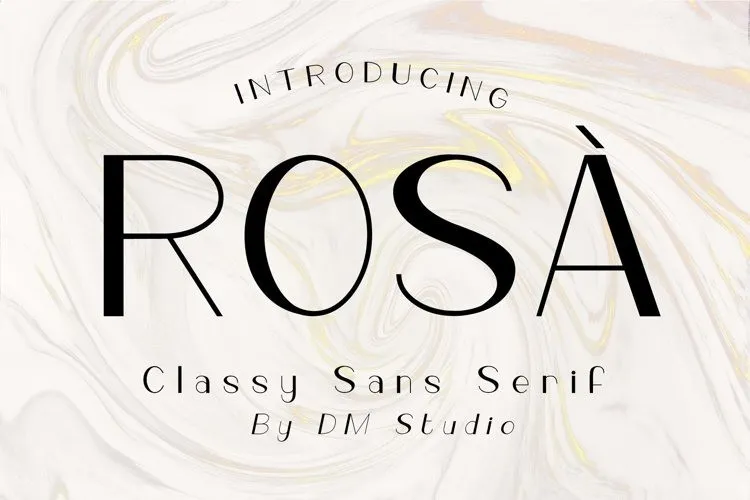
A Rosà Sans Serif Font é uma elegante seleção para designers atentos ao estilo moderno. Desenhada por dmletter31, esta fonte sans-serif traz cada letra cuidadosamente desenvolvida para manter seu texto único e chamativo. Com linhas limpas e desenhadas com cuidado, ela se destaca em diversos formatos de logotipos, marcas, headlines e templates, adaptando-se perfeitamente a qualquer tópico de marketing ou propaganda. Seja você um criador de logomarcas sofisticados ou simplesmente buscando adicionar um toque fresco à sua próxima peça editorial, Rosà Sans Serif Font oferece uma solução para todos os seus desafios de design. Além disso, a fonte tem duas versões disponíveis: regular e itálica, permitindo que você escolha a opção que melhor se adequa ao seu projeto específico. Sem necessidade de programas especializados, Rosà Sans Serif Font é fácil de integrar em qualquer projeto para torná-lo ainda mais brilhante e personalizado.